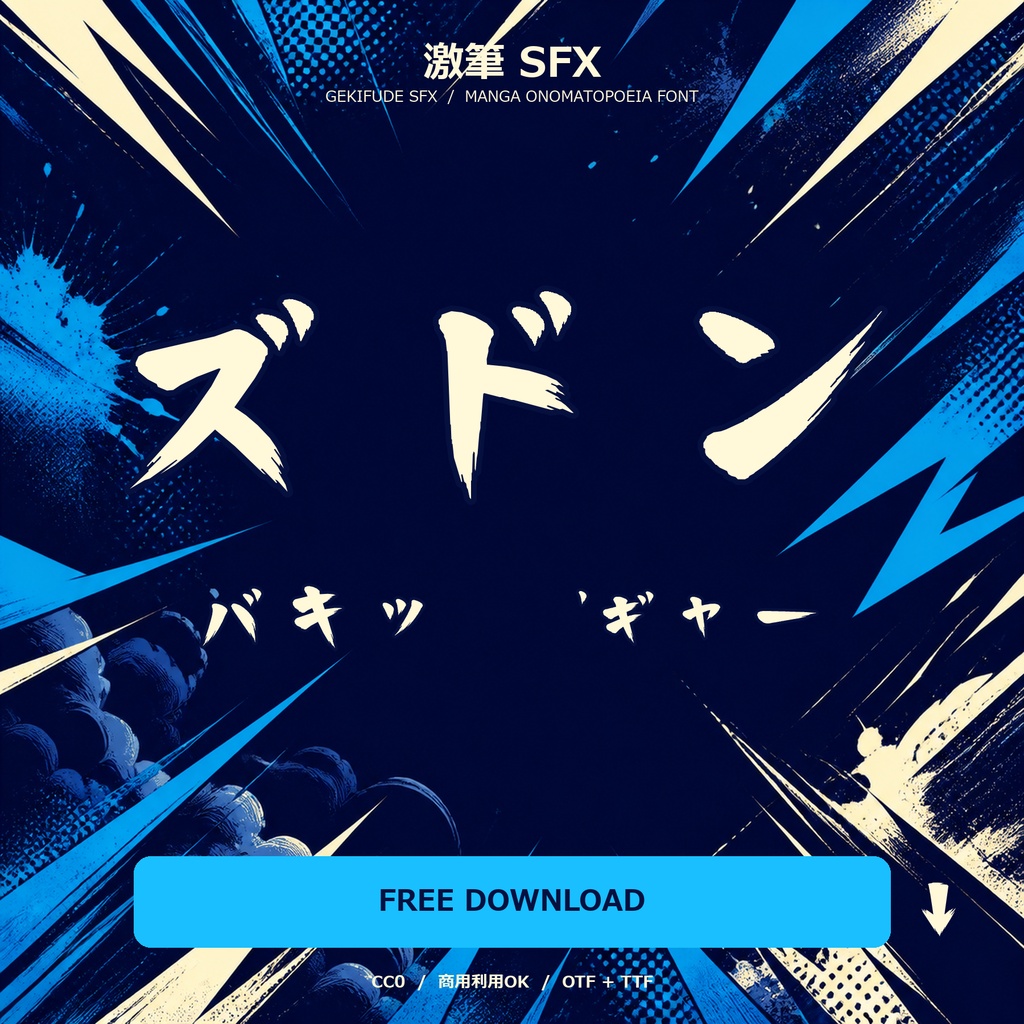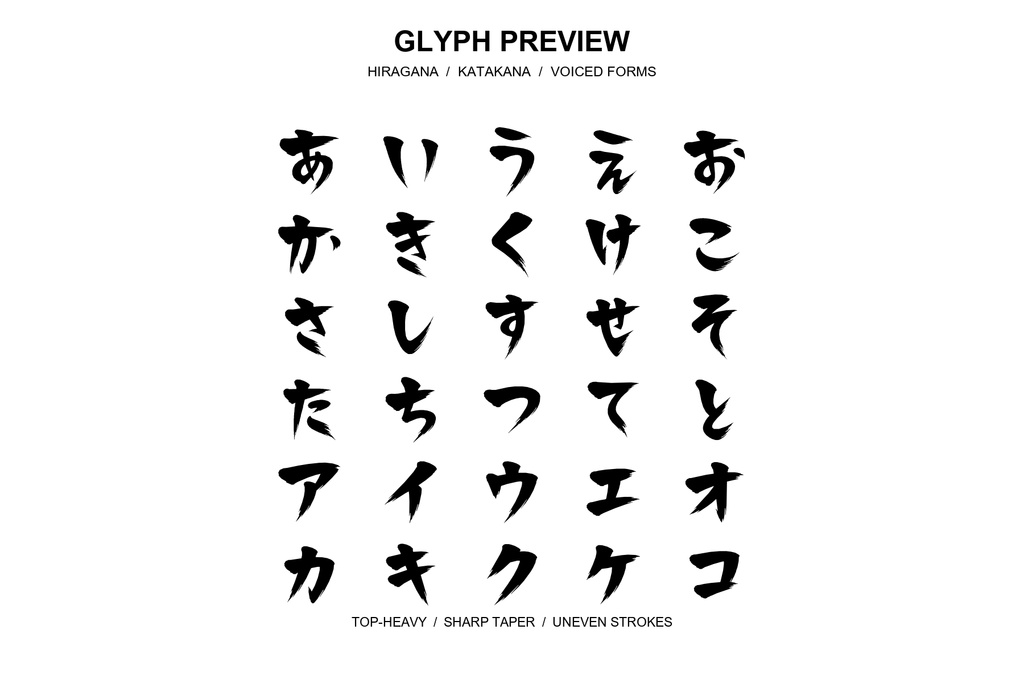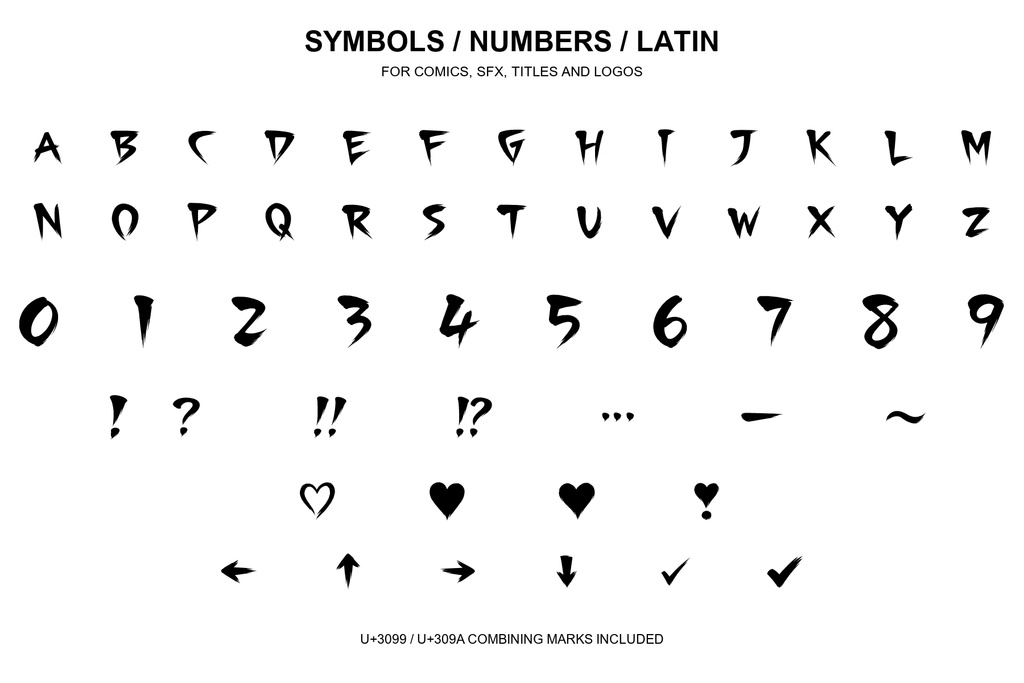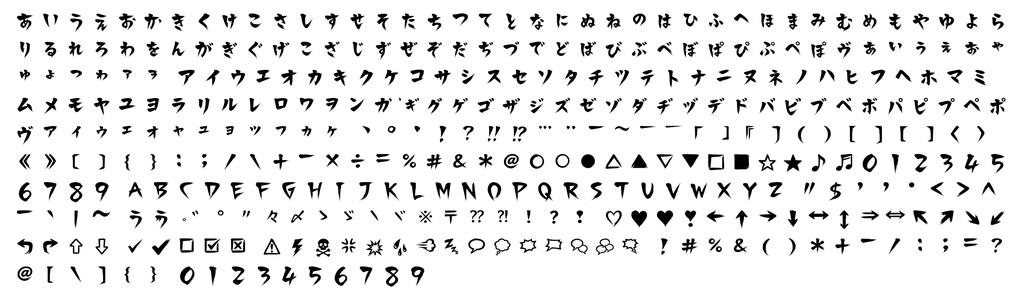
【更新のお知らせ】 激筆SFXを v1.004 に更新しました。 今回の更新では、カタカナ「ガ」「ギ」の濁点が混ざって表示される不具合を修正しています。TTF版・OTF版の両方を更新しました。 その他の文字や仕様に変更はありません。旧版をご利用の方は、最新版を再ダウンロードしてください。ご指摘・ご報告ありがとうございました。 激筆 SFX フォント 漫画・コミックのオノマトペ、効果音、叫び声、衝撃表現のために制作した、攻撃的な筆文字フォントです。 文字上部を大きく広げ、下部へ向かって鋭くすぼめた、逆三角形に近いシルエットが特徴です。太く重い始筆、鋭く長い払い、不均一な線幅によって、文字そのものから音や勢いを感じられるデザインを目指しました。 ■ 主な用途 漫画、同人誌の効果音/オノマトペ/叫び声/動画/ゲーム/配信画面/サムネイル/ロゴ/タイトル/印刷物 ■ 収録内容 ひらがな、カタカナ、濁音、半濁音、小書き文字 英大文字 A~Z、半角・全角数字 ASCII記号、日本語句読点、括弧 ハート、矢印、チェック、漫画用の衝撃・感情記号 スピーチバブル関連記号 結合濁点 U+3099、結合半濁点 U+309A Unicode登録:364コードポイント 総グリフ数:361 スタイル:Regular ※漢字、英小文字、Bold、Italicは収録していません。 ■ フォント形式 GEKIFUDE-SFX-Regular.otf GEKIFUDE-SFX-Regular.ttf 通常はOTF版を推奨します。OTFとTTFを同時にインストールする必要はありません。 ■ 動作確認 WindowsおよびAdobe Photoshopで確認しています。 縦書きや結合濁点などのOpenType機能は、使用するアプリケーションによって動作が異なる場合があります。 ■ ライセンス CC0 1.0 Universal / No Rights Reserved 個人利用、商用利用、改変、加工、再配布、フォントデータの販売を含め、自由に使用できます。利用申請、作者への連絡、クレジット表記は不要です。 作者:HIDEOUT フォント名:激筆 SFX フォント / GEKIFUDE SFX バージョン:1.002 ■ 内容物 フォント本体(OTF・TTF)、README、LICENSE、収録文字一覧、チェックサム ■ 注意事項 本フォントは現状のまま提供されます。本フォントの使用によって生じた損害について、作者は責任を負いません。